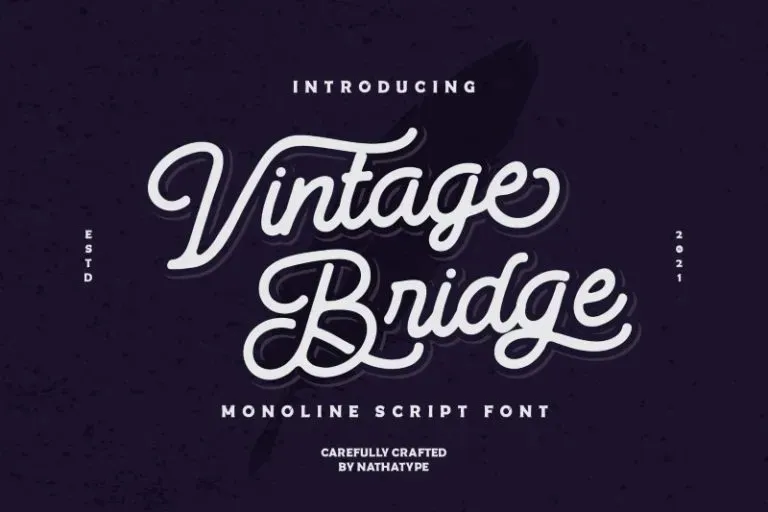
A Vintage Bridge Font é uma escolha perfeita para quem busca unir elegância com dinamismo na sua tipografia. Criada à mão e cheia de conceitos refinados, ela mantém um formato vibrante que confere beleza singular ao design. Ideal tanto para banners em redes sociais, postagens e anúncios impressos quanto para criações personalizadas como cartazes, etiquetas ou embalagens. Também pode ser usada como overlay moderno sobre qualquer imagem de fundo, criando um toque único que aprimora o impacto visual. Esta fonte é perfeita para quem deseja dar vida aos seus materiais e criar uma conexão emocional com seu público através dos textos. Ela faz você se destacar e atrair olhares nas redes sociais, ou mesmo fazer sua mensagem se firmar na impressão.